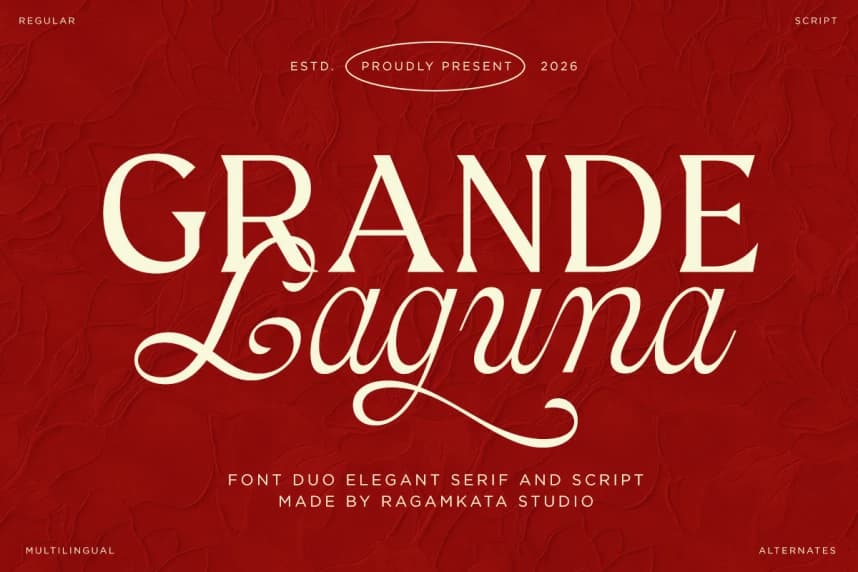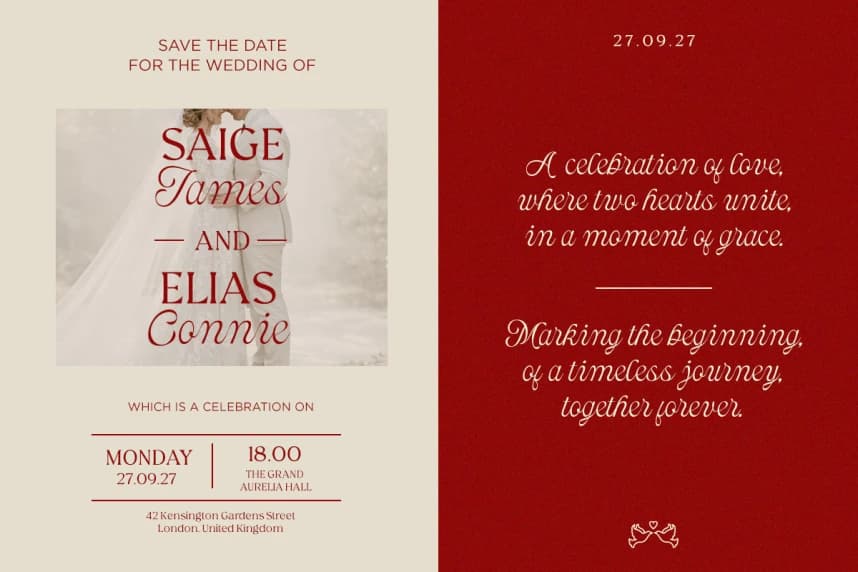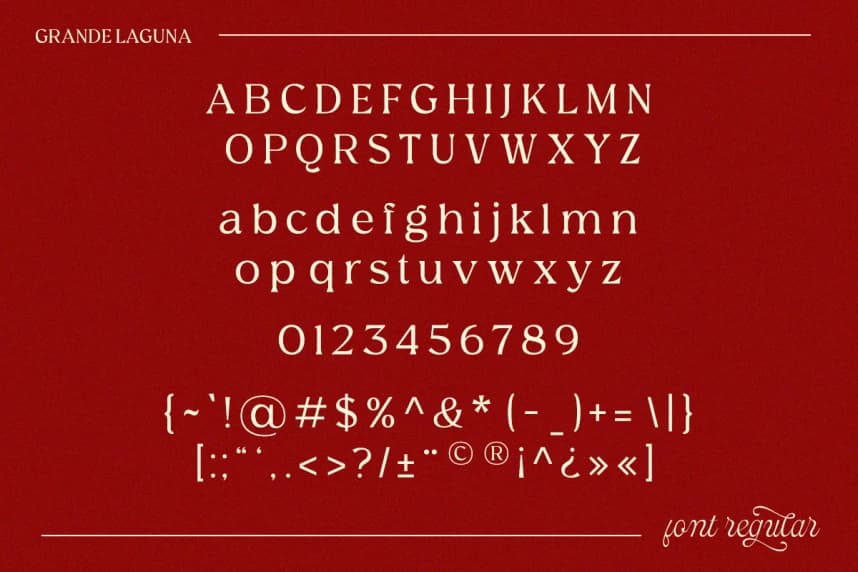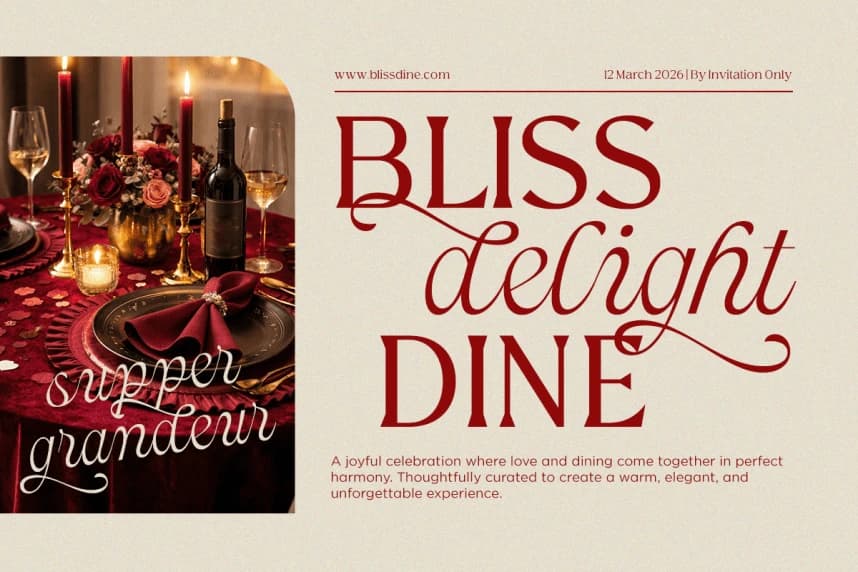
Grande Laguna Font
Grande Laguna Font, rafine bir serif ile zarif bir el yazısı stilini güzelce harmanlayan zarif bir font ikilisidir. Yapı ile akıcılık arasında uyum yaratmak üzere tasarlanmıştır ve lüks ile zamansız bir estetik sunar; herhangi bir tasarımı anında yükseltir.
Grande Laguna Font zarif bir font ikilisi olup, zarif bir serif ile akıcı bir scripti güzelce harmanlar. Yapı ile akıcılık arasında uyum yaratmak için tasarlanan bu font, lüks ve zamansız bir estetik sunar ve herhangi bir tasarımı anında yükseltir.